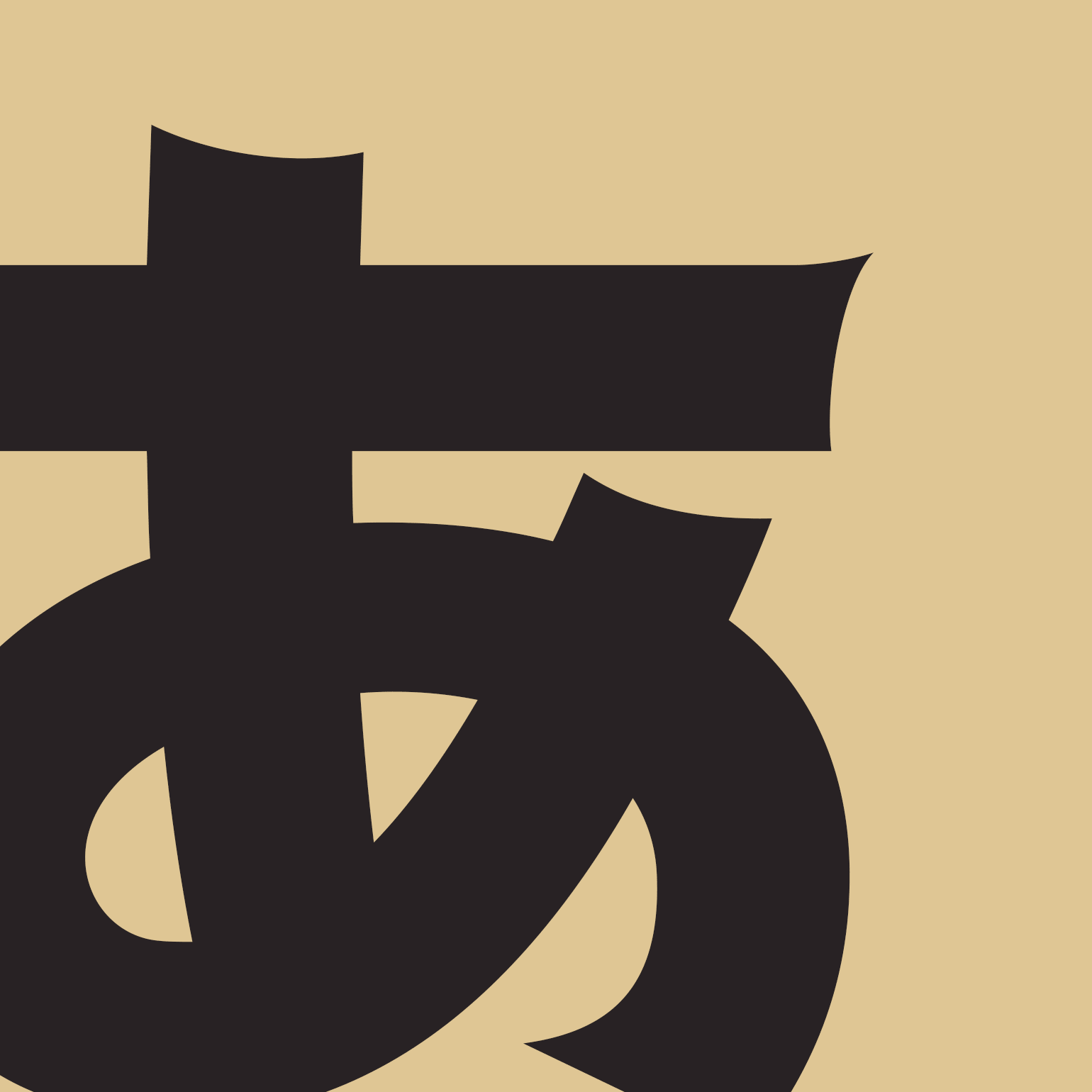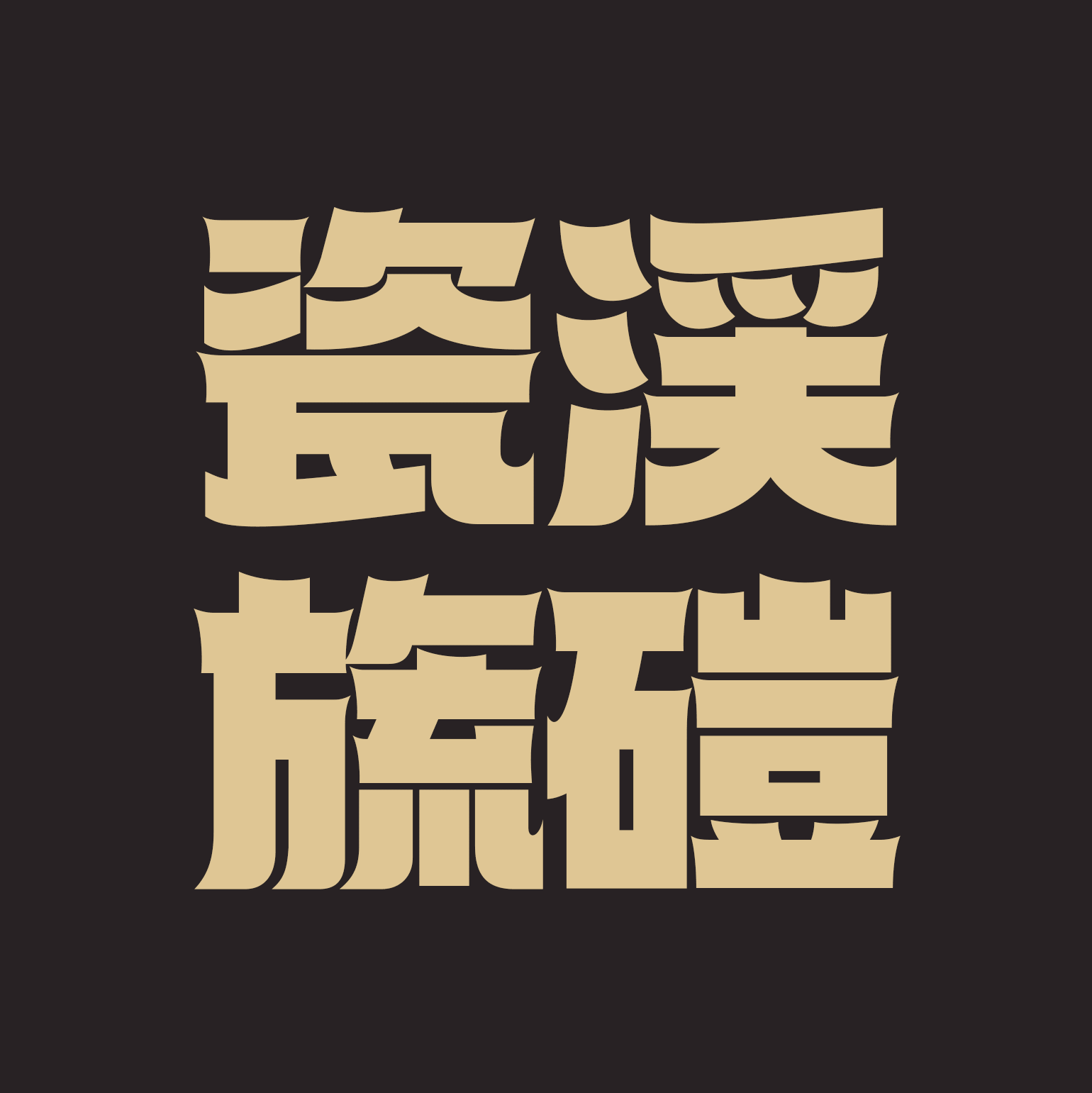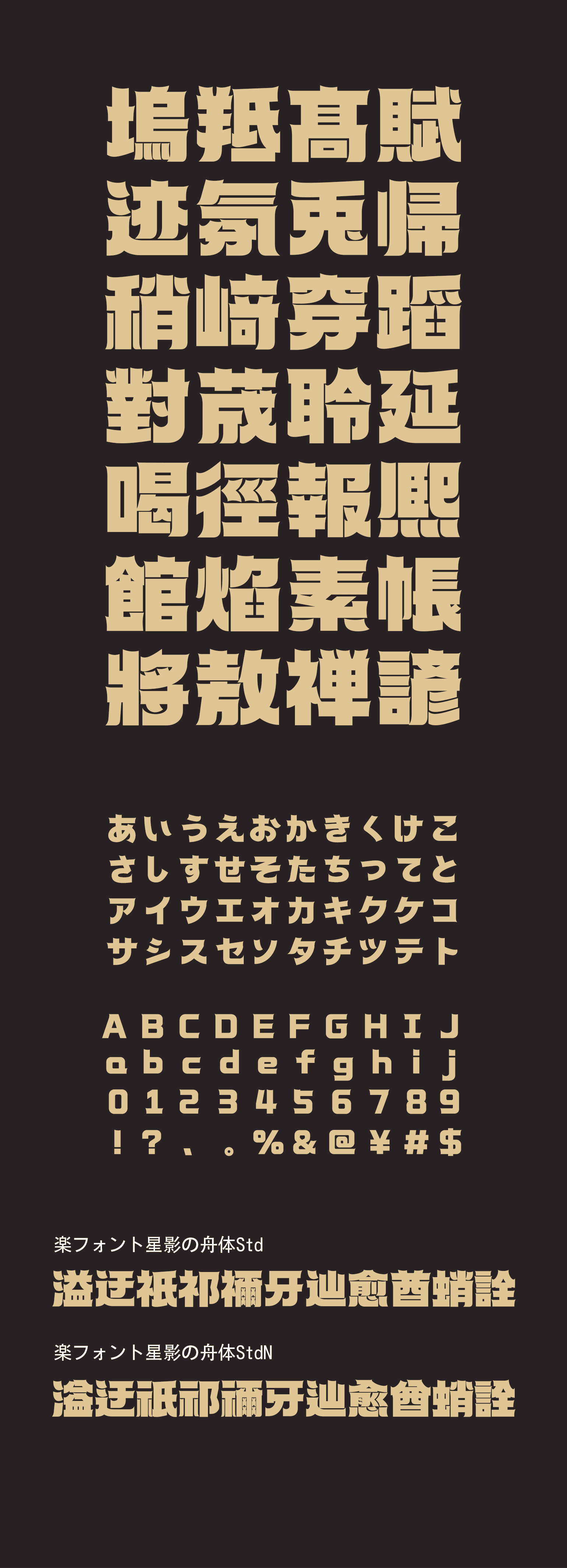
星影の舟体(ほしかげのふねたい)
極太の筆画とやわらかなコーナーにより、力強さと親しみ
やすさをあわせ持つフォントです。ふくらみのある字形が
存在感を生み、丸み処理が重さをやわらげて読みやすさを
高めます。タイトルやパッケージ、サイン、広告など、明
快なインパクトと信頼感を伝えたい場面に最適です。